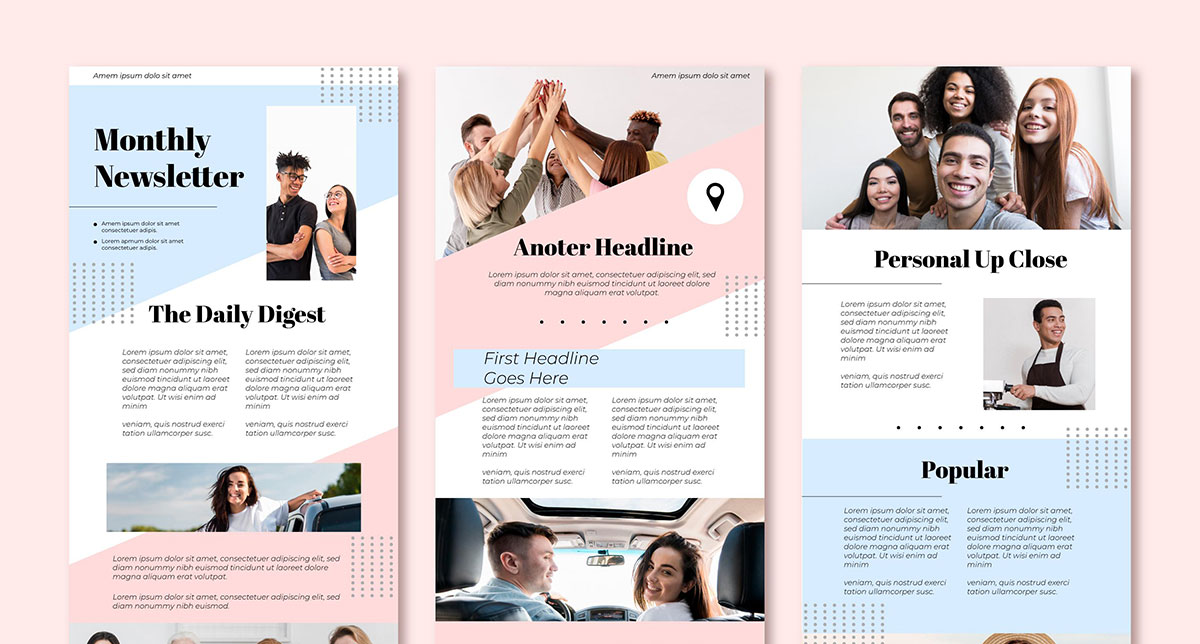
Stellen Sie sich vor, Sie erstellen einen E-Mail-Newsletter, der Ihr Publikum fesselt, bevor es auch nur ein Wort liest. Wie? Die richtige Wahl der Schriftarten.
Typografisch gesehen sind die von Ihnen gewählten Schriftarten die stillen Botschafter Ihrer Marke und vermitteln Feinheiten, die das Engagement des Lesers stärken oder schwächen können.
In diesem digitalen Bereich, in dem Posteingänge überlaufen und die Aufmerksamkeitsspannen schwinden, ist die Nutzung der besten Schriftarten für Newsletter ein echter Game-Changer.
Es geht nicht nur um Ästhetik; es geht darum, die visuelle Hierarchie, die optimale Zeilenlänge und die Psychologie der Typografie zu nutzen, um Markenkonsistenz zu wahren und die Lesbarkeit zu erhöhen.
Am Ende Ihrer Reise werden Sie Geheimnisse entdecken, um das Benutzerengagement durch Typografie zu verstärken – ein Toolkit aus Schriftarten, bereit dazu, die Stimme Ihrer Nachricht fein abzustimmen.
Erwarten Sie nicht nur Schriftarten zu entdecken, sondern auch responsive Design-Techniken und wichtige Aspekte wie Web-sichere Optionen und zugängliche Typografie, die sicherstellen, dass Ihr Inhalt auf jedem Gerät strahlt.
Werfen Sie einen Blick unter die Haube, während wir Typografie im E-Mail-Marketing, die Rolle von Schriftartenkombinationen und warum mobilfreundliche Schriftarten in der heutigen schnelllebigen digitalen Welt das Zepter in der Hand halten, entschlüsseln.
Die besten Schriftarten für Newsletter
SchriftartennameVerfügbarkeitDesignstilEinsatzmöglichkeitenBesondere Merkmale
RobotoSehr verbreitetSans-serifFließtext, ÜberschriftenModern, geometrisch, freundlich
Open SansSehr verbreitetSans-serifFließtext, Überschriften, BildunterschriftenOptimiert für Lesbarkeit, neutral
RalewayVerbreitetSans-serifÜberschriften, ZwischenüberschriftenElegant, mit einem einzigartigen ‚w‘
GeorgiaSehr verbreitetSerifFließtext, ÜberschriftenEtwas breiter, bildschirmfreundliche Serifen
VerdanaSehr verbreitetSans-serifFließtext, Überschriften, BildunterschriftenEntwickelt für Bildschirmlesbarkeit
HelveticaVerbreitetSans-serifÜberschriften, BildunterschriftenKlassisches, neutrales Design
Times New RomanSehr verbreitetSerifFließtext, ÜberschriftenDie Standardwahl für gedruckte Dokumente
ArialSehr verbreitetSans-serifFließtext, ÜberschriftenWeit verbreitet, neutral
Franklin GothicVerbreitetSans-serifÜberschriften, ZwischenüberschriftenStarker, robuster Charakter
TimesSehr verbreitetSerifFließtext, ÜberschriftenKlassisches Erscheinungsbild, gut für den Druck
CenturyVerbreitetSerifFließtext, ÜberschriftenLesbar, elegant
PerpetuaWeniger verbreitetSerifFließtext, ÜberschriftenElegant mit hohen Aufstrichen
AkzidenzWeniger verbreitetSans-serifÜberschriften, ZwischenüberschriftenDer Vorläufer von Helvetica
AvenirVerbreitetSans-serifFließtext, ÜberschriftenModern, geometrisch
ClarendonWeniger verbreitetSerifÜberschriften, ZwischenüberschriftenStarker, klassischer Design
Beste Schriftarten für E-Mail-Newsletters
Wenn es um E-Mail-Newsletters geht, spielen Sie auf dem digitalen Spielfeld. Ihre Schriftart muss klar, auf allen Geräten lesbar sein und natürlich gut aussehen. Hier sind einige Top-Picks:
Roboto
Ah, der Klassiker! Es ist wie das Schweizer Taschenmesser der Schriftarten – vielseitig und modern. Ein echter Geheimtipp.
Open Sans
Freundlich, aber professionell, es ist wie der freundliche Nachbar unter den Schriftarten. Super lesbar auch.
Raleway
Dünnes Gewicht, großzügiger Abstand, es ist wie der elegante Cousin in der Schriftfamilie. Groartig für einen anspruchsvollen Touch.
The Dreamer Font
Diese Schrift ist etwas, wenn Sie Ihrer Nachricht eine persönliche Note geben möchten. Sie ist spaßig, einzigartig und trotzdem super lesbar.
Radona
Redet man über Modernität! Diese Schriftart schreit geradezu „Hightech“ und ist perfekt für Marken, die auf der Höhe der Zeit sein wollen.
Miamo Font Family
Vielseitigkeit ist hier das Stichwort. Mit verschiedenen Gewichten ist sie sowohl für Überschriften als auch für Fließtext perfekt geeignet.
Ideale Schriftarten für gedruckte Newsletters
Der Druck ist ein ganz anderes Spiel. Sie müssen darüber nachdenken, wie die Schrift einmal auf Papier aussieht. Hier sind einige solide Auswahlmöglichkeiten:
Radiograph
Stilvoll und lesbar. Es ist eine Serifenschrift, die eine Note von Klasse vermittelt, ohne die Klarheit zu opfern.
Fast & Cure
Diese serifenbetonte Schrift ist ausdrucksstark und macht eine Aussage ohne zu schreien.
Briston
Kondensiert, aber klar. Sie ist großartig für Überschriften und nutzt Ihren Platz optimal aus.
Georgia
Ein Klassiker! Es ist wie diese vertrauenswürdige alte Jacke – sieht immer gut aus und enttäuscht nie, besonders im Druck.
Verdana
Entworfen für Klarheit auf dem Bildschirm, aber raten Sie mal? Es funktioniert auch auf Papier. Klar, lesbar und angenehm für die Augen bei längeren Texten.